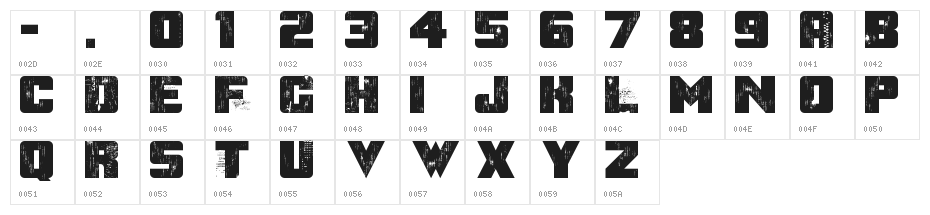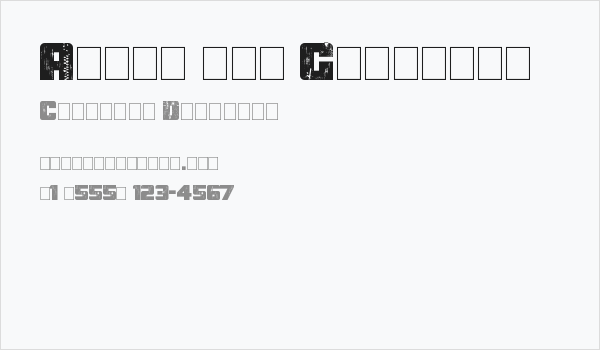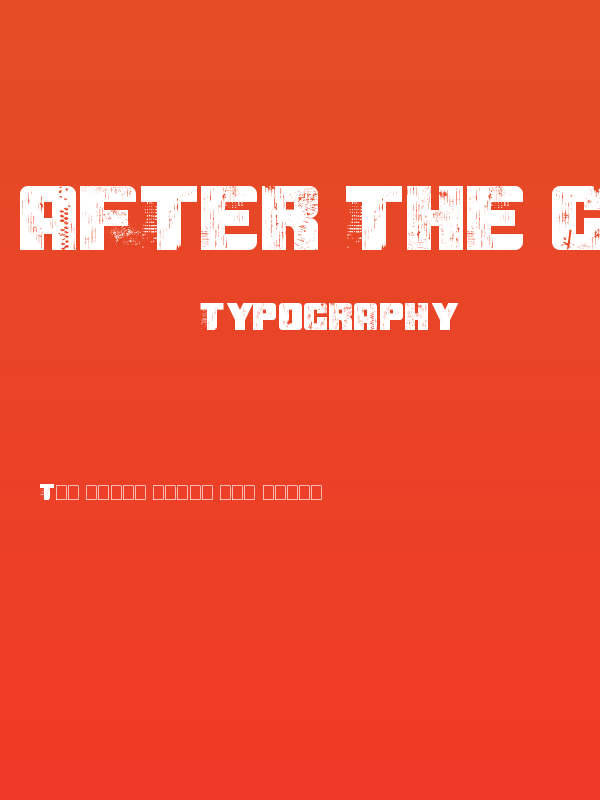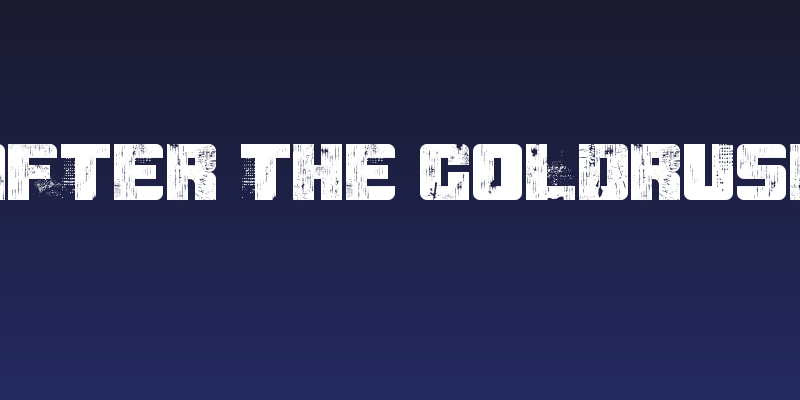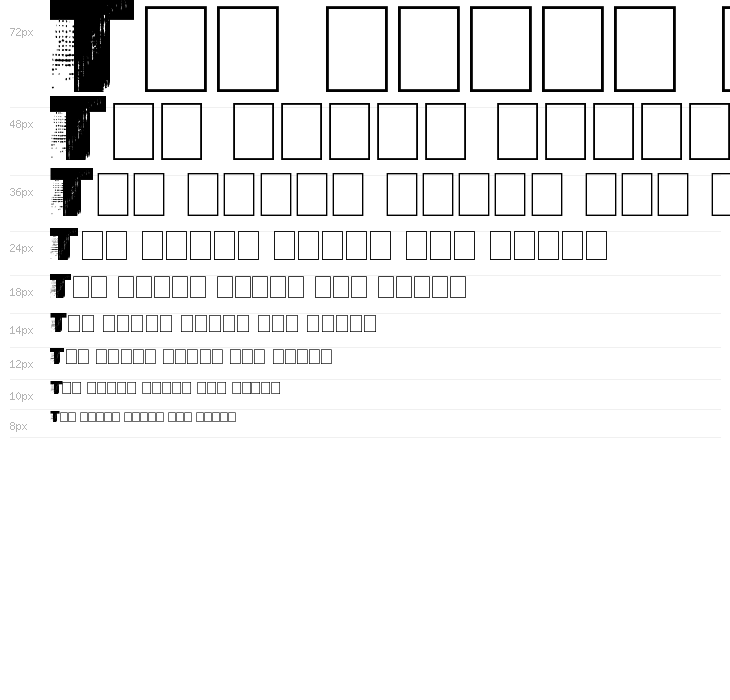
After the Goldrush Font
| Progetti proposti | Ideal for posters, album covers, branding for outdoor or adventure-related products, and vintage-themed designs. |